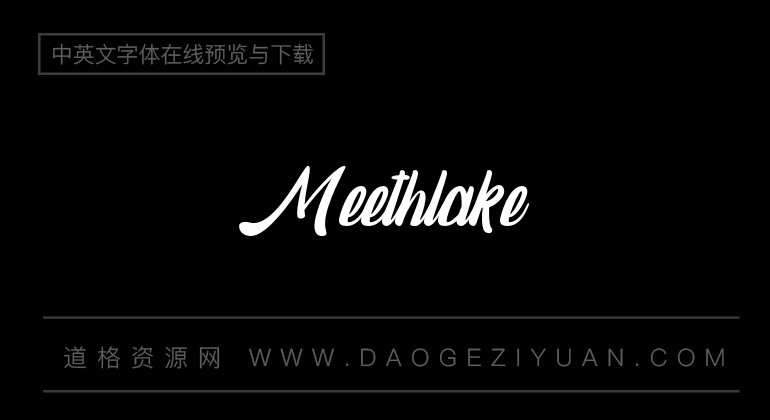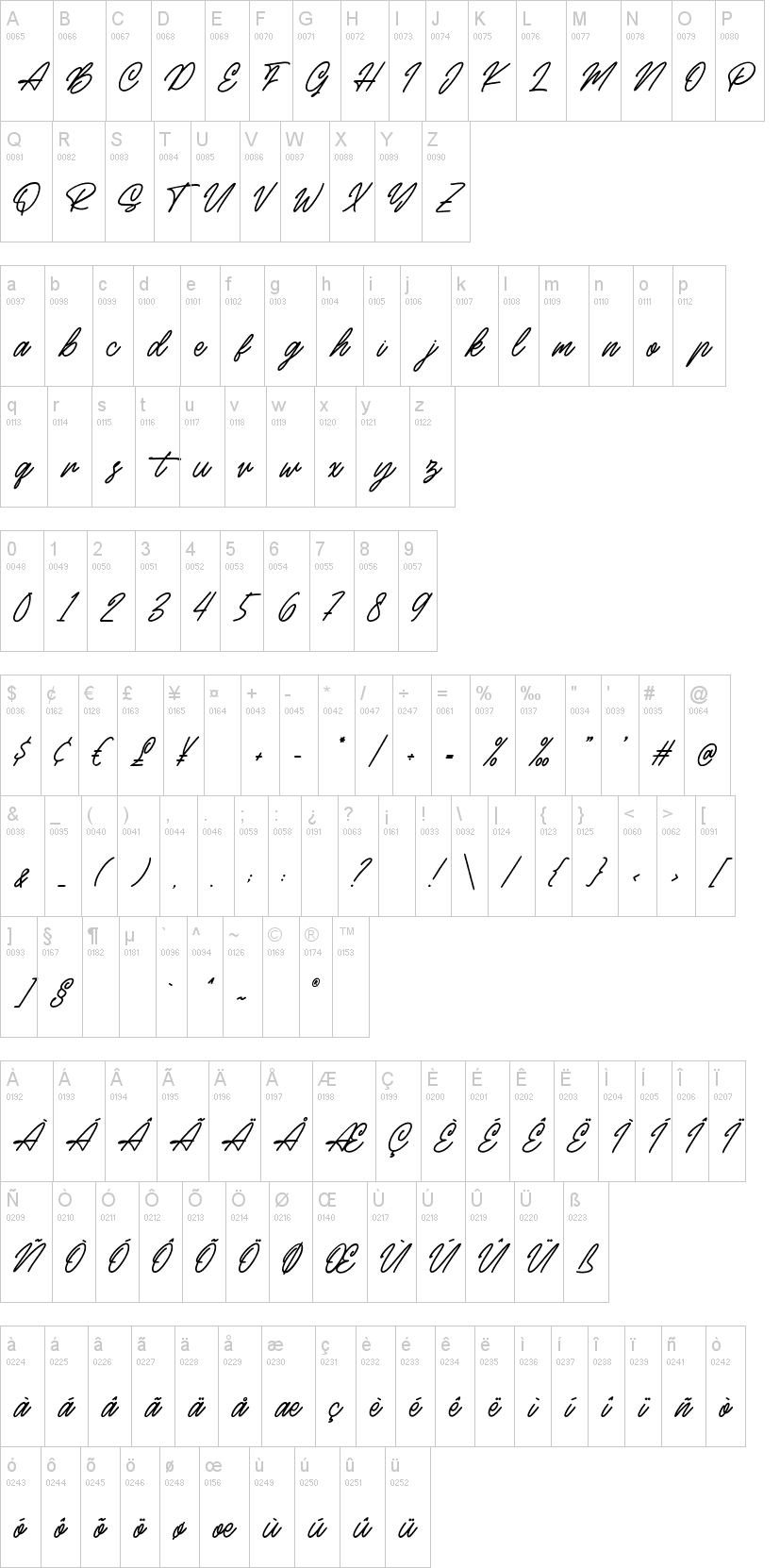
Meethlake 是一款简洁、清新的英文字体,由著名的英国设计师 Paul Lloyd 创作,是一款优雅、现代的字体,具有良好的可读性和细节表现力。Meethlake 字体拥有多种字体风格,包括细体、粗体、等宽体、斜体等,以及多种字号,可以满足不同的设计需求。Meethlake 字体拥有清晰的线条,更加易于阅读,适合用于各种平面设计,如标题、文字、海报等。内容介绍
Meethlake是一款非常不错的手写艺术字体,具有很好的视觉感,适合于文化类的宣传设计、商业类品牌的广告和产品包装设计以及个性化文字排版等较多场景。